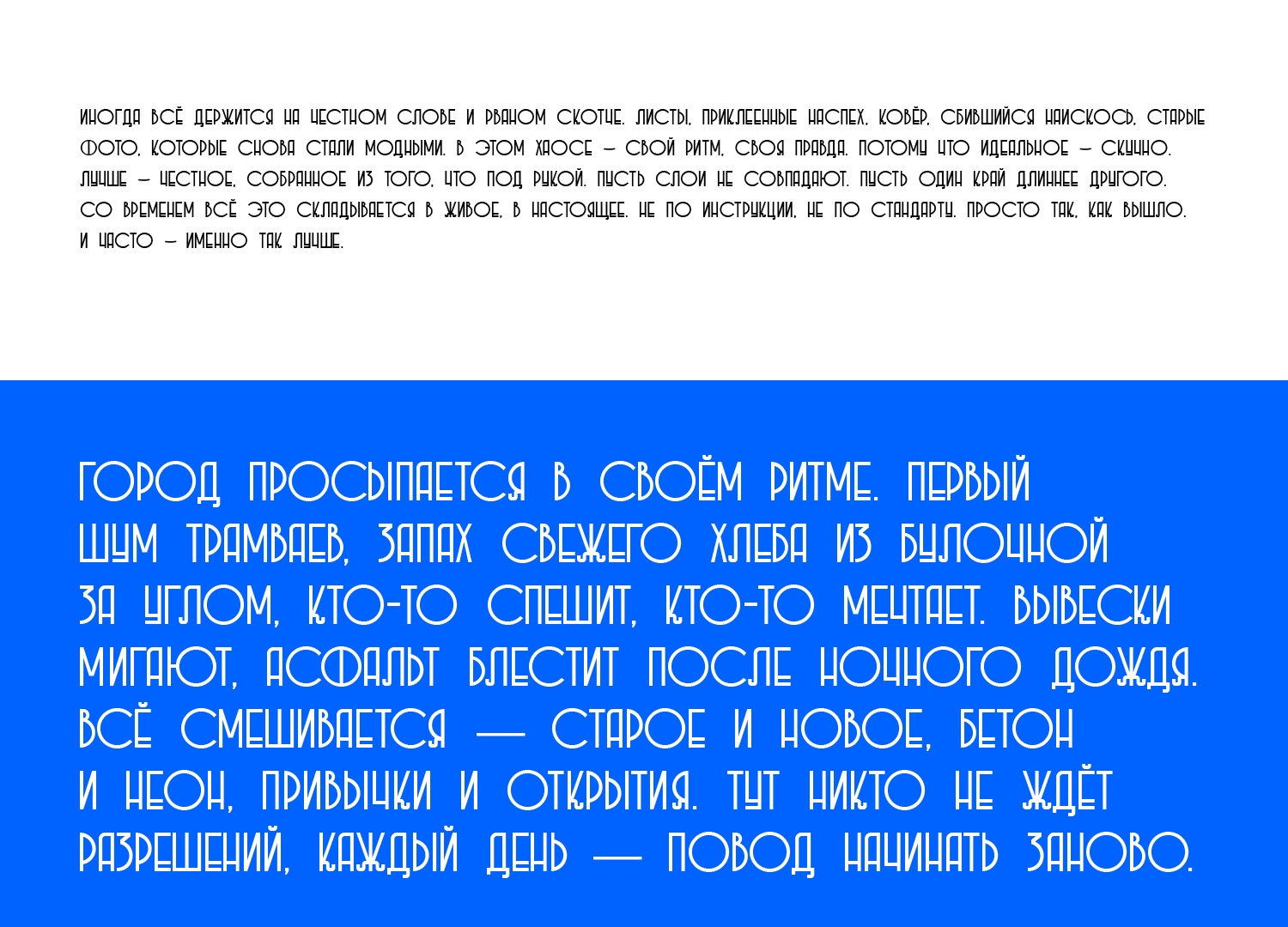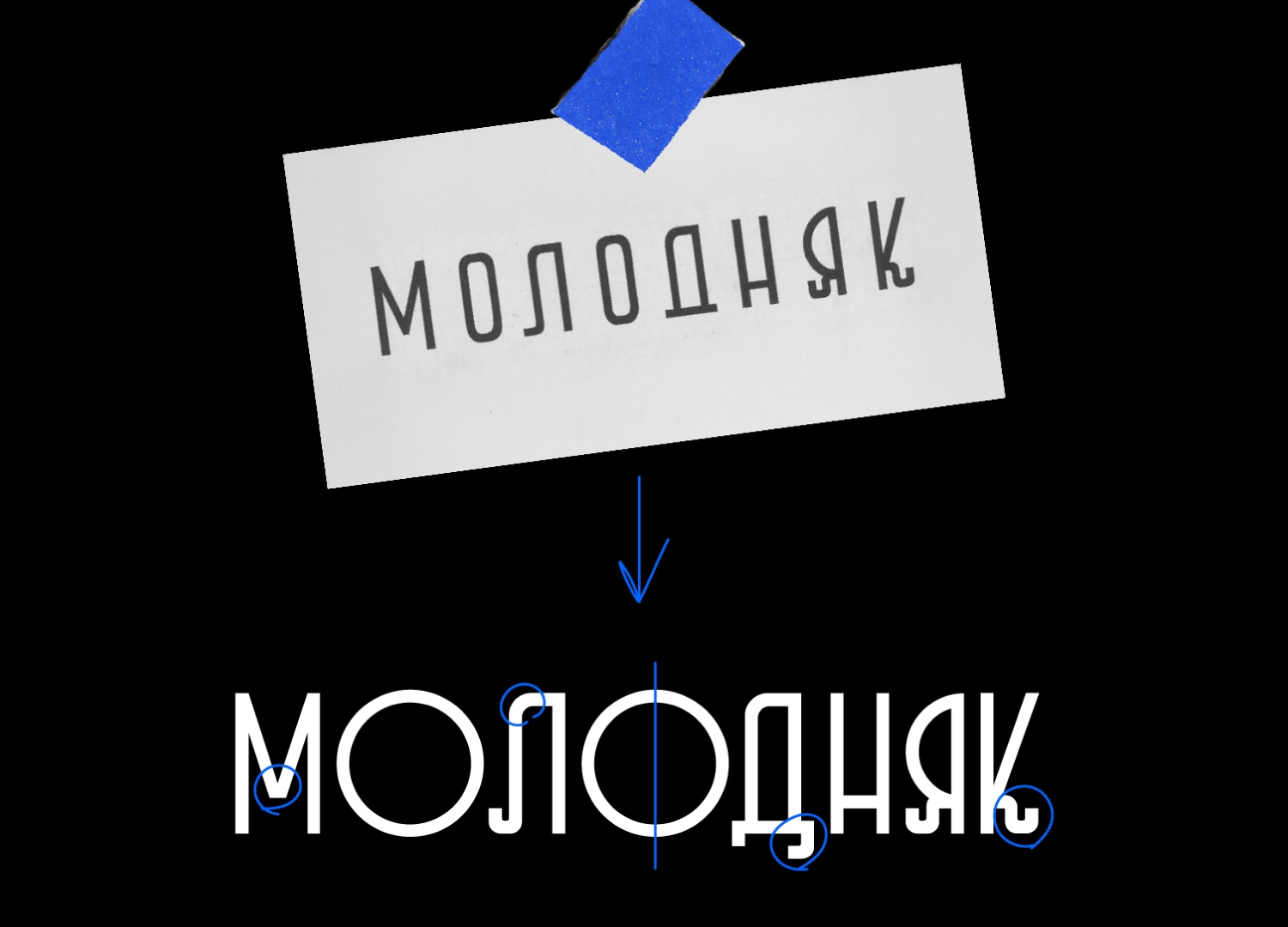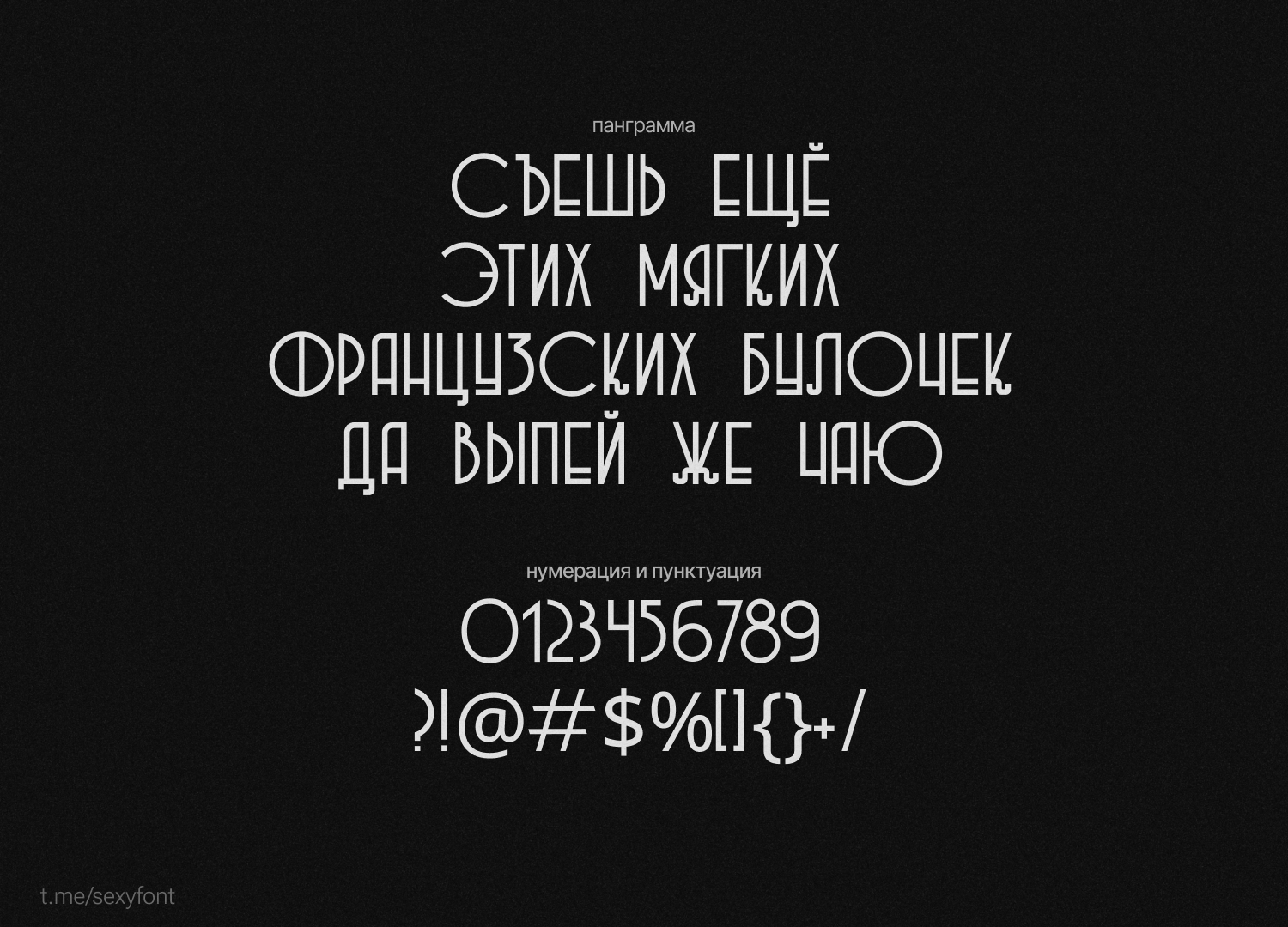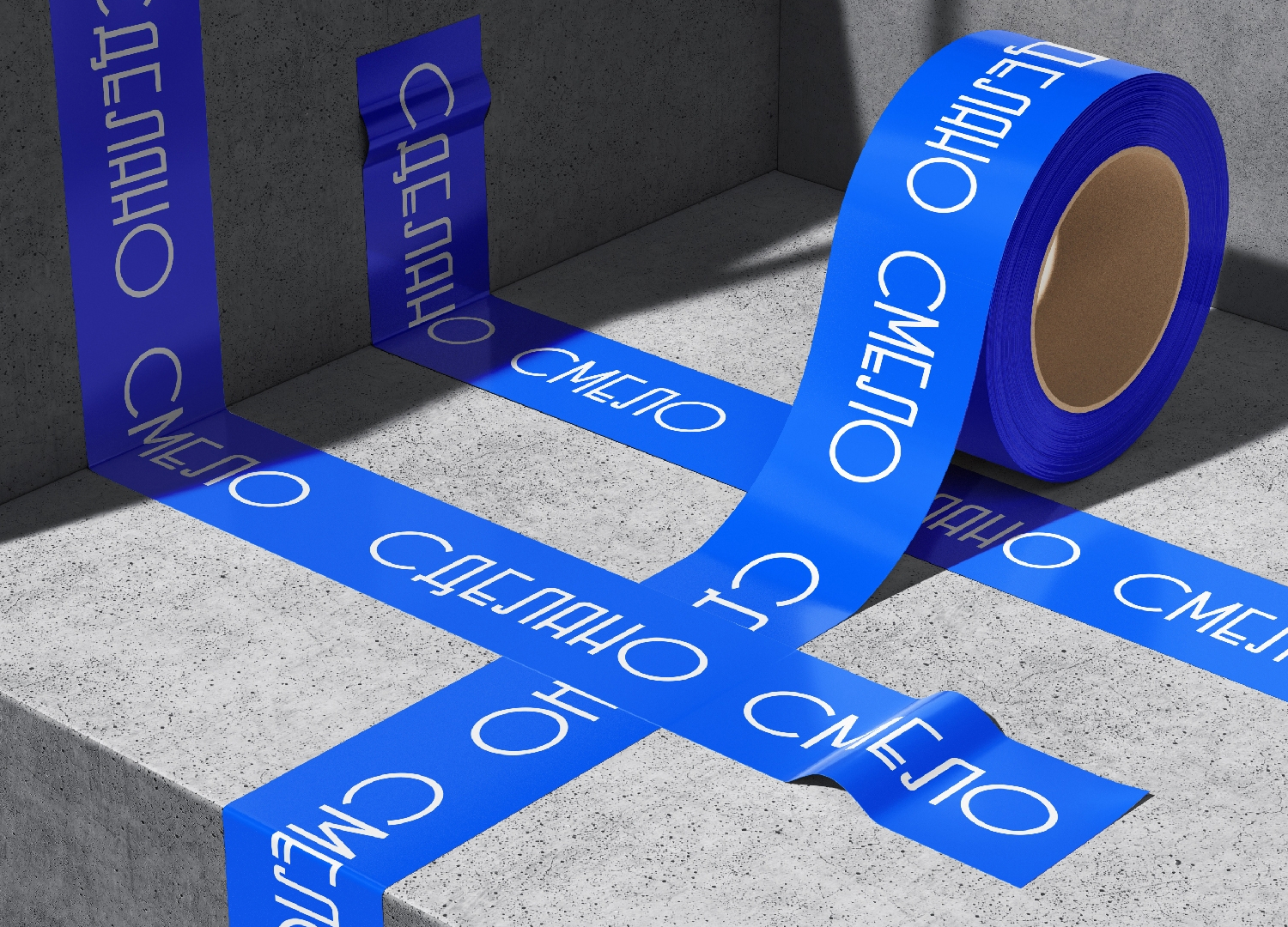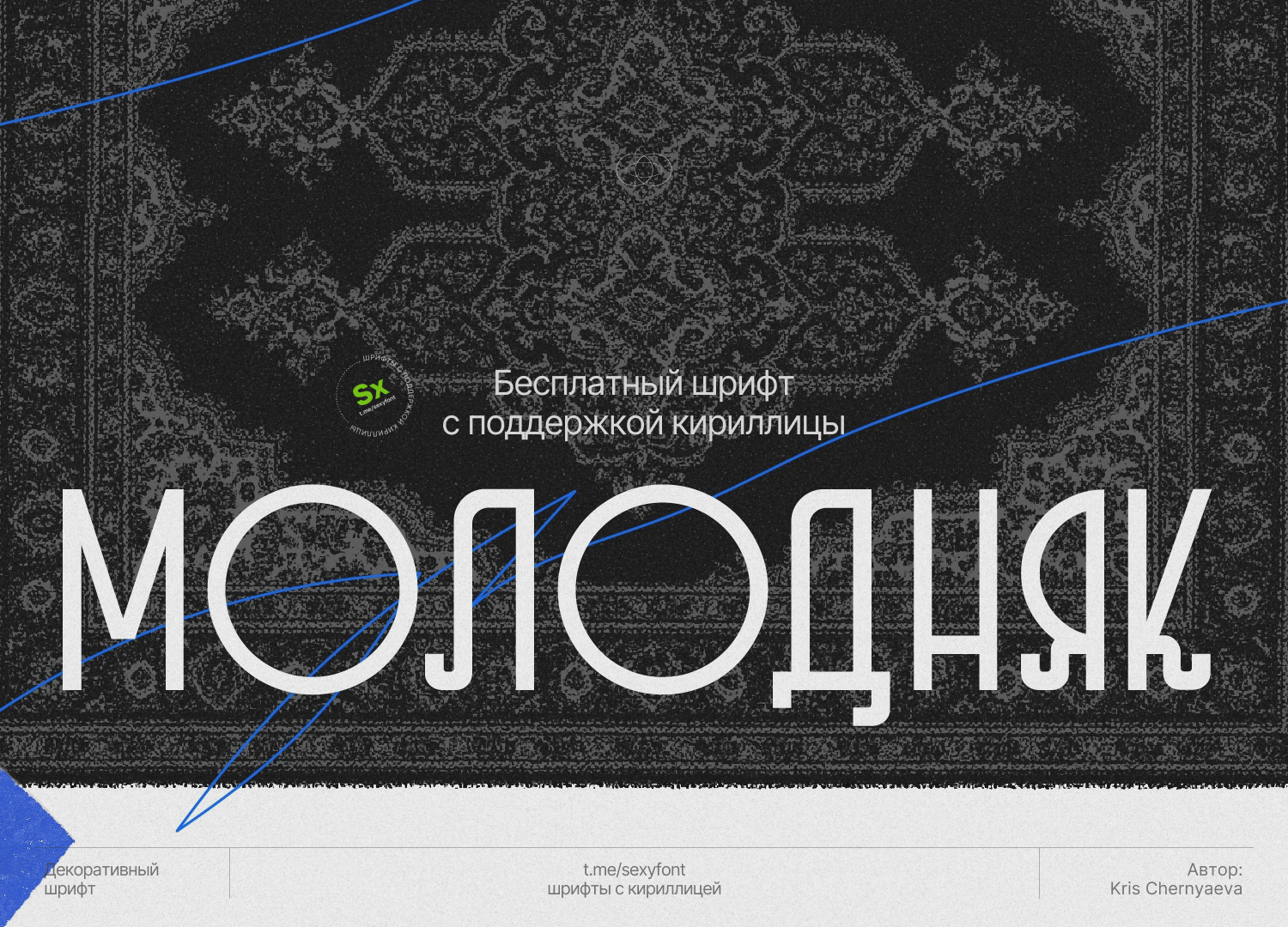
Бесплатный Шрифт Молодняк (Molodnyak)
Шрифт Молодняк (Molodnyak) Экспериментальный гротеск, вдохновленный советский леттерингом. В основе дух молодого авангарда, стремление к новому и уважение к визуальной культуре прошлого